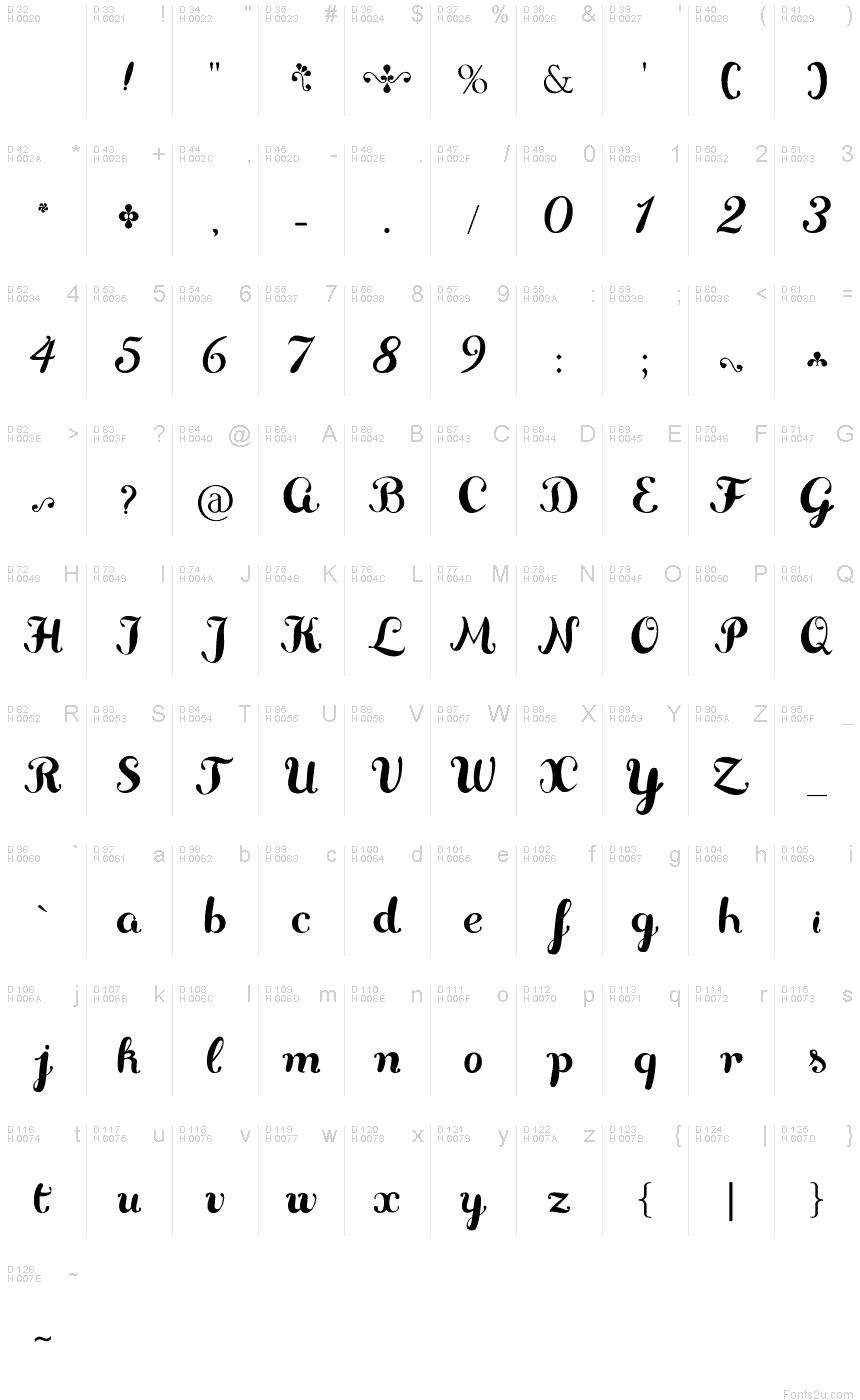
Delikatessen to darmowy odręczny krój pismowy typu script. Wszelkie prawa zastrzeżone, narysowany z dramatycznym kontrastem kaligraficznym i wyraźnym nachyleniem w prawo. Długie, zapętlone wielkie litery nadają znakom wyrafinowaną ozdobność.
Opakowania modowe i papeteria boutique mogą wykorzystać jego elegancki zamaszysty styl do etykiet, zaproszeń i redakcyjnych nagłówków okładkowych. Te same formalne krzywe pasują również do menu restauracyjnych i identyfikacji wizualnej słodyczy. Przemówi do projektantów pracujących dla odbiorców z branży luksusowej, ślubnej lub rzemieślniczej żywności.